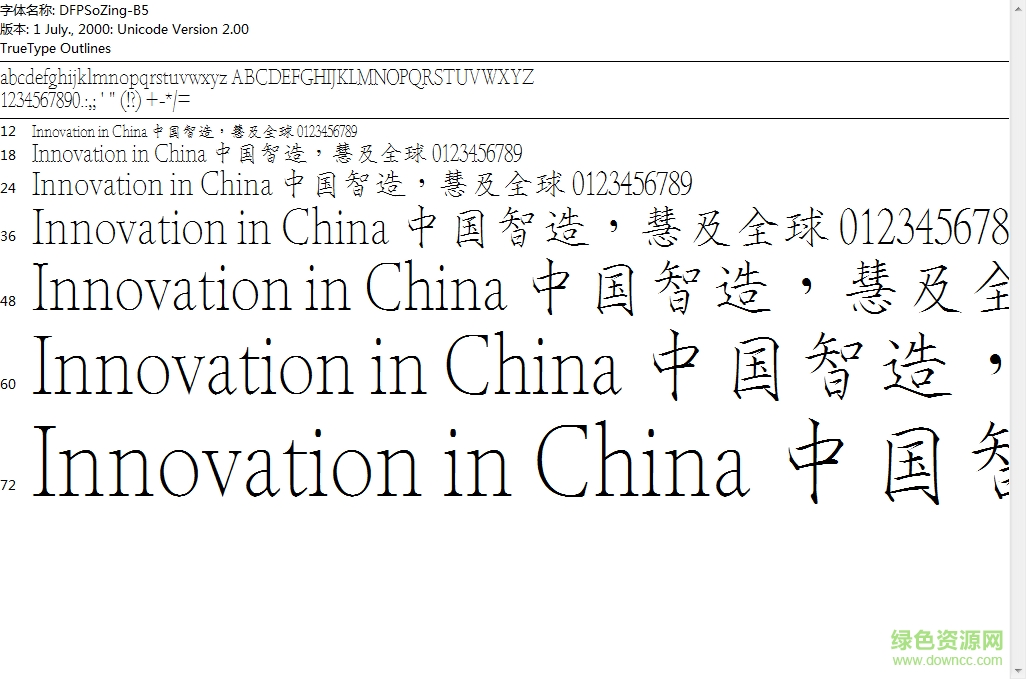
軟件介紹 軟件標簽: 華康字體 字體 華康瘦金體繁是一款簡約清新的繁體字體,此款字體筆畫偏細、大小均勻,整體效果非常不錯,廣泛應用于排版印刷、廣告設計、文本編輯等領域,喜歡的朋友歡迎來綠色資源網下載!字體安裝方法方法一:控制面板/字體/文件/安裝新字體;方法二:直接將字體復制到C:\WINDOWS\Fonts。方法三:針對win7系統(tǒng),用戶只需選中字體右鍵安裝即可。注意事項本站所有字體資源僅供個人學習與參考,如需商業(yè)使用請到相關官網授權。 軟件截圖 上一張下一張(1 / 1) 安裝詳細截圖 猜你喜歡 手機字體 瘦金體 手機字體 手機字體是智能手機常用的字體。每款手機都有自己默認的字體,如果你不喜歡,可以更換成自己喜歡的字體類型,這個時候就需要下載對應的手機字體了,有需要的朋友,趕快下載體驗吧! 查看更多>> 牽牛花繞青藤體 7.05M/中文/10.0/下載 伯樂丫丫體手機字體 2.02M/中文/10.0/v1.0 安卓版下載 伯樂花香體 2.06M/中文/10.0/下載 暖色君小威體字體 7.70M/中文/10.0/下載 字體管家喜氣羊羊 8.85M/中文/10.0/下載 字體管家喬喬體 3.14M/中文/10.0/下載 瘦金體 瘦金體又稱徽宗體,是由宋徽宗趙佶所創(chuàng)的一款字體,該字體用筆暢快,筆跡瘦勁,結構緊湊,可以廣泛應用于排版印刷、廣告設計、文本編輯等領域! 查看更多>> 字體管家瀟灑瘦金體 5.26M/中文/0.0/下載 漢儀瘦金體字體 10.00M/中文/2.5/ttf下載 吳邪瘦金體 3.41M/中文/9.3/下載 宋徽宗瘦金體 2.65M/中文/10.0/ttf下載 漢儀瘦金書 4.21M/繁體/10.0/下載 漢儀瘦金書簡字體 2.86M/中文/5.0/免費版下載 其他版本下載 標題 大小 更新日期 下載 下載地址 電腦版 華康瘦金體繁體 點擊報錯 軟件無法下載或下載后無法使用,請點擊報錯,謝謝! 關閉報錯反饋 請描述您所遇到的錯誤,我們將盡快予以修正,謝謝! *必填項,請輸入內容 本類最新 華康漆隸體繁w5 wow魔獸世界華康少女字體ttf 免費版 華康蕓風體w3 繁體 華康pop2體w9 p 華康粗黑體繁 dfpyuanw7字體 ttf版 相關文章 Photoshop字體安裝使用方法和技巧 如何解決“無法新增字體”問題 Win 7系統(tǒng)安裝字體方法 網頁字體大小設置方法 怎么改網頁字體大小 在Linux系統(tǒng)中安裝字體的幾種方法 windows7字體顯示問題:打開某些程序的時候顯示的是亂碼 用戶評論 熱門評論 最新評論 發(fā)表評論 查看所有評論(0) 昵稱: 請不要評論無意義或臟話,我們所有評論會有人工審核. 字數: 0/500 (您的評論需要經過審核才能顯示)